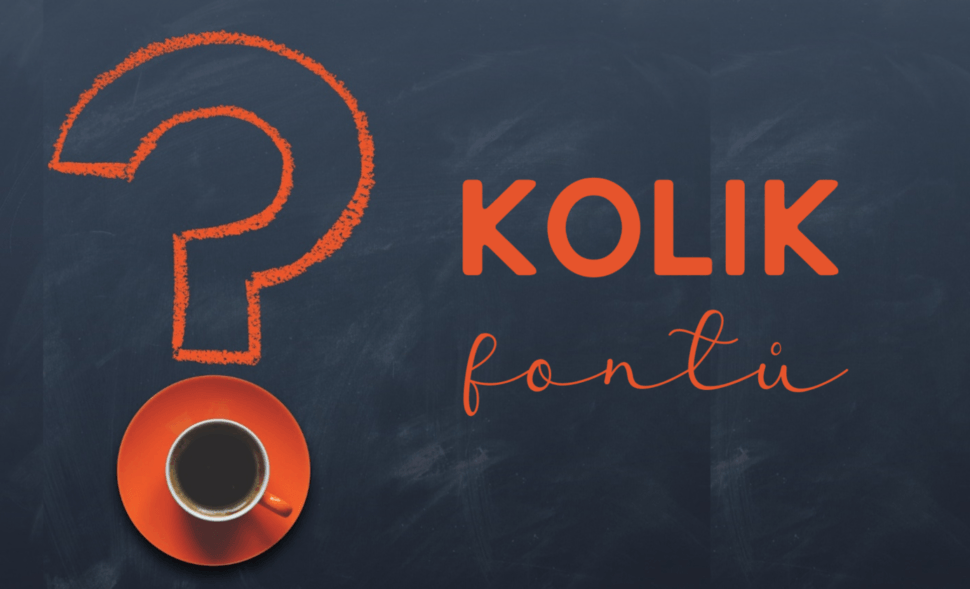
Na jednoduchou otázku jednoduchá odpověď. Každý lepší grafik a webdesigner vám řekne „maximálně 3“. Ale 90% lidí toto číslo vůbec nepomůže.
Existuje přímá úměra mezi vaším charakterem a postojem k podnikání a počtem fontů, které na webu použijete. Jsou lidé, kteří nutně potřebují více fontů, jeden nemá šanci pokrýt jejich potřeby. A pak jsou jiní, kteří si klidně vystačí s jedním jediným, naopak, více fontů v nich budí dojem chaosu. Jenom pozor, pokud říkáme jeden font, znamená to, že ho použijeme opravdu všude. Nejenom na blogu a úvodní stránce, ale i v dalších typech textů napříč celým webem.
I na sebejednodušším webu totiž máme různé druhy textů, které nám právě písmo umožní krásně strukturovat, zviditelnit, upozadit, atd. A naopak, všechny tyto texty je potřeba brát jako celek a nepoužívat pro každý z nich jiný font. Jsou to například:
Často vídám weby, na kterých je jiný font v body textu a jiný v patičce. Nebo menu má úplně samostatný font, který se nevyskytuje nikde na webu. Občas mají lidé potřebu dávat na tlačítka tučný font nezávislák, který nemá nic společného se zbytkem. Takové fonty navíc nedávají smysl.
Na druhou stranu jsou změny fontů (nebo jeho řezu), které smysl dávají a mají své opodstatnění. Třeba taková kurzíva. Určitě si vybavíte, že pro citáty často používáme kurzívu, která krásně citát oddělí od zbytku textu a mozku signalizuje přímou řeč.
„Font, použitý na webu nebo na vizitce, vyjadřuje osobitost, ovlivňuje vnímání a dokresluje celkový dojem. Má moc přitáhnout ty správné klienty a odradit ty ostatní.“
(Vsuvka pro #typonazi: ano, v tomto článku používám slovo FONT úplně blbě, jako synonymum slova PÍSMO. Důvody to má dva. Jednak je tento článek určený pro lidi, kteří většinou vůbec netuší, jaký je mezi těmito slovy rozdíl. A druhý důvod je, že si chci ulehčit práci. A abych šířila i osvětu, určitě doporučuji přečíst si článek Písmo nebo font.)
Na základě mých zkušeností ze 6 let konzultací se stovkami lidí jsem zjistila, že lidé se podle výběru fontů dají rozdělit do jasně vymezených skupin. Jakou na ně použijete typologii je celkem jedno. Jiné fonty budou vybírat extroverti, jiné introverti. Jiné fonty budou vybírat lidé typu země, jiné typu vzduch. Jiné fonty použije archetyp Hrdiny, jiné Milenec. V typologii podle fontů jsem vytvořila tyto skupiny:
A jak uvidíte dál v článku, každá z těchto skupin bude inklinovat k jinému počtu fontů. Praktičtí a efektivní zůstanou u jednoho, Přemýšliví a zodpovědní budou potřebovat někdy i dva, Vnímaví a starostliví minimálně dva plus emoční kotva a Autentickým někdy rebelům často nestačí ani tři. Pokud vás zajímá do které patříte vy, zkuste Fontokvíz – typologii osobnosti podle výběru fontů.
Pojďme se tedy podívat na to, jaké máte možnosti, pokud si vyberete 1 font, 2 fonty anebo se rozšoupnete a budete používat 3 fonty.
Kdy si bohatě vystačíte s jedním fontem v různých velikostech?
Rozhodně, pokud patříte do skupiny Praktičtí a efektivní. Fonty nemáte potřebu řešit, vyznáváte minimalismus, sázíte na efektivitu, nebo máte paniku z toho, abyste neporušili nějaká psaná i nepsaná pravidla estetiky, webdesignu a kdovíčeho ještě. Když se budete chtít rozšoupnout, použijete kurzívu nebo bold. I když zůstaneme u jednoho písma, vyplatí se pracovat minimálně s jeho velikostí a řezem. Jinak vám čtenář brzy vezme nohy na ramena.
Další možné situace, kdy se hodí zůstat u jednoho fontu:
Když chcete sázku na jistotu, sáhněte do kategorie bezpatkového písma (sans serif). Použít ale můžete klidně i patkové (serif), pokud jste praktiční, ale efektivita ustupuje na úkor přemýšlivosti. A pokud váháte mezi patkovým a bezpatkovým písmem, Slab serif je skvělý kompromis.
V rámci kategorie „1 font“ samozřejmě můžete měnit řezy a velikosti. Viz ukázky.
P.S. To, že patkové písmo se na web nehodí, je fakt mýtus. Mrkněte se třeba k Františkovi Štormovi, jaké skvosty u něj najdete v patkových písmech určených pro online.
VARIANTA BEZPATKOVÁ – SANS SERIF
VARIANTA PATKOVÁ – SLAB SERIF
VARIANTA PATKOVÁ – SERIF
Ukázka, jak se dá krásně pracovat s jedním písmem na webu:
Kdy potřebujete 2 fonty?
Máte rádi všechno v cajku, netoužíte vnášet do textu extra emoce, ale i tak máte potřebu s textem pracovat a dát mu víc rozměrů. Budete se pohybovat klidně napříč jednou rodinou fontů a zvládnete použít i dva různé fonty. Můžete patřit do skupiny Přemýšliví a zodpovědní, kde potřebujete skvělou čitelnost, ale zároveň špetku hloubky. V tomto případě budete vybírat s největší pravděpodobností nějakou z jednodušších kombinací (viz VARIANTA JEDNODUCHÁ v ukázkách).
Anebo jste z kategorie Vnímavých a starostlivých a potřebujete do textu vnést emoce, například péči, jemnost, ženskost, vřelost… „Obyčejné“ serif nebo sans serif fonty vás v tomto ohledu úplně neuspokojí, potřebujete i písmo, které není tak odtažité, profesionální nebo přímé. V tomto případě vás budou přitahovat pro nadpisy i ručně psané písmo nebo jemné nadpisové fonty anebo budete vyhledávat nenápadnější harmonické kombinace (viz VARIANTA HARMONICKÁ a VÝRAZNÁ v ukázkách).
Jenom je potřeba uvědomit si, kde můžete své kreativitě dát průchod a kde se to nehodí. A jak je všechny vhodně zkombinovat.
Tak, už je vám jasnější, kolik fontů na web potřebujete? Jestli vám stačí jeden, nebo nutně potřebujete tři? A že je úplně v pořádku, že pokud jste dula, tak to můžete mít jinak než mladý ajťák, který vám dělá web? On si vystačí s jedním Google fontem, vy potřebujete minimálně dva, abyste se na stránkách cítila sama sebou.